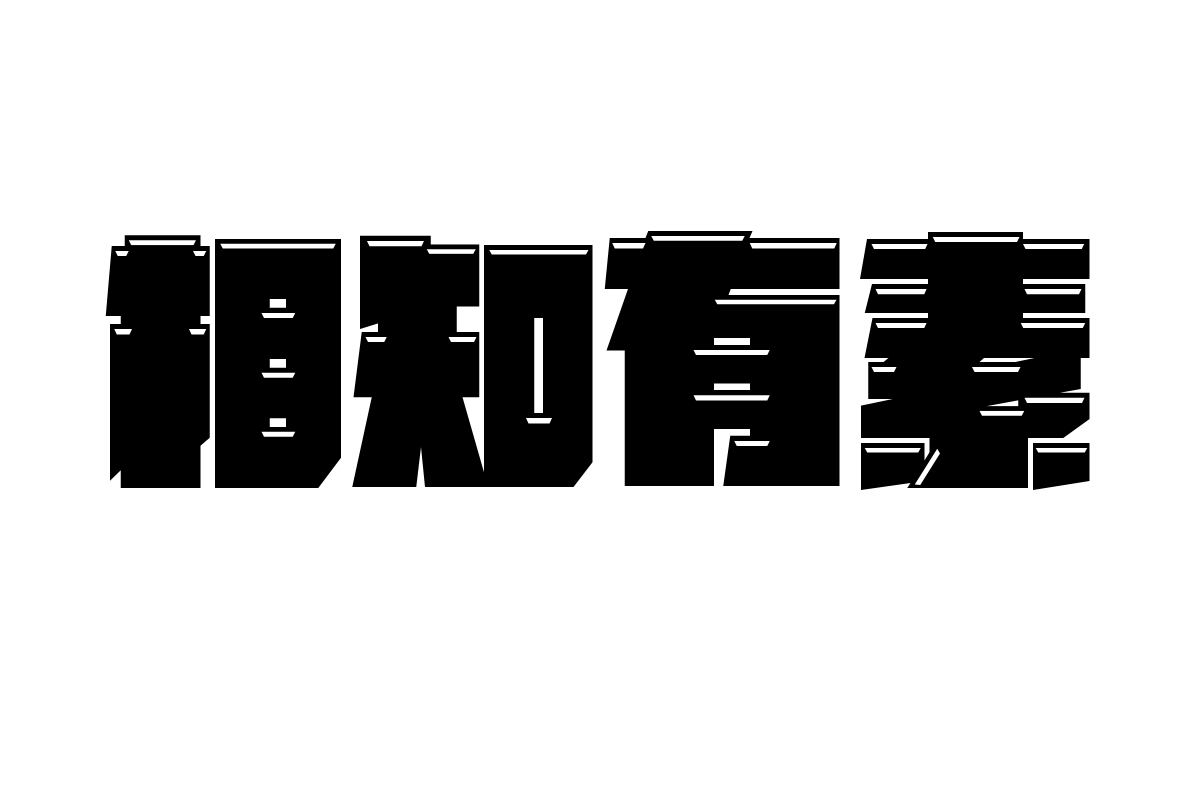
锐字机甲洪荒超级光是一款具有强烈视觉冲击力的字体,其特点如下:
1. 设计独特:该字体采用了独特的机甲元素,将传统汉字与机械结构相结合,创造出一种全新的视觉效果。
2. 字形饱满:锐字机甲洪荒超级光的字形饱满有力,线条流畅,给人一种强烈的视觉冲击感。
3. 笔画粗细分明:该字体的笔画粗细分明,既有粗犷的线条,又有细腻的笔触,使得整体视觉效果更加丰富。
4. 易于辨识:由于其独特的设计,锐字机甲洪荒超级光在视觉上具有较高的辨识度,方便用户快速识别。
5. 应用场景广泛:该字体适用于各种需要强调视觉效果的场合,如广告、海报、网页设计等。
总之,锐字机甲洪荒超级光是一款极具创意和视觉冲击力的字体,适合用于需要突出个性和表现力的设计项目。